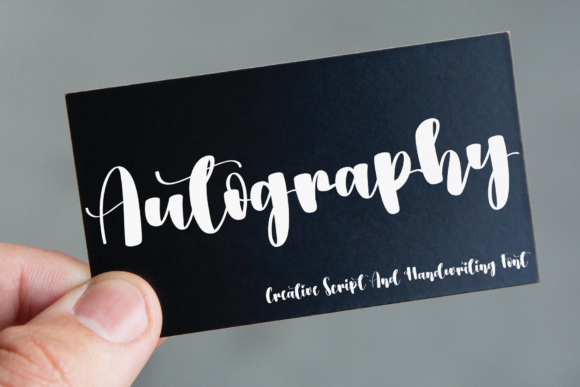
Autography
หากคุณกำลังมองหาเนื้อหาคุณภาพสูงเช่น Autography แพ็คเกจพรีเมียมนี้เป็นตัวเลือกที่ยอดเยี่ยมสำหรับโปรเจ็กต์สร้างสรรค์ของคุณ
สร้างขึ้นอย่างแม่นยำ Autography ให้เวกเตอร์ที่สะอาด พิมพ์ตัวอักษรที่ราบรื่น และใบอนุญาตเชิงพาณิชย์เพื่อความสบายใจ
ไม่ว่าคุณจะสร้างผลิตภัณฑ์ POD (Print on Demand) คำเชิญงานแต่งงาน หรือกราฟิกโซเชียลมีเดีย Autography ก็เหมาะสมอย่างยิ่ง